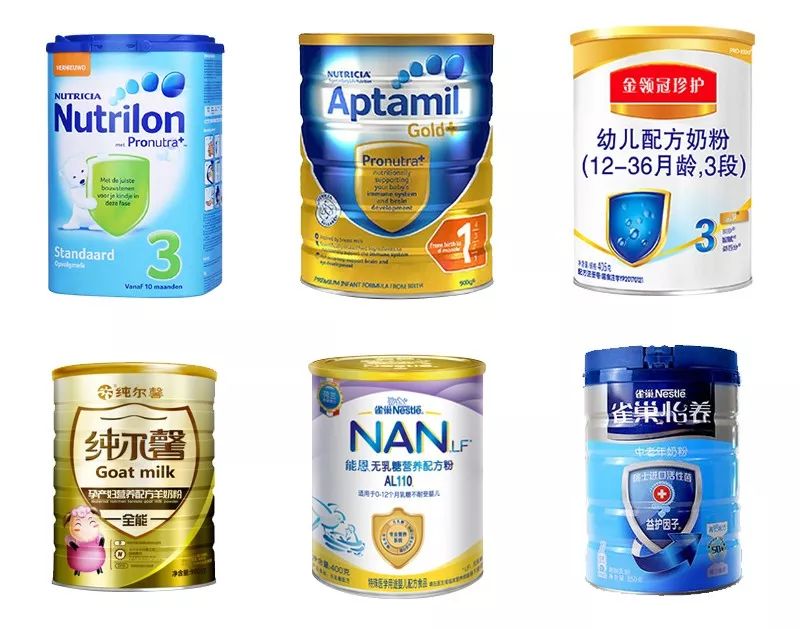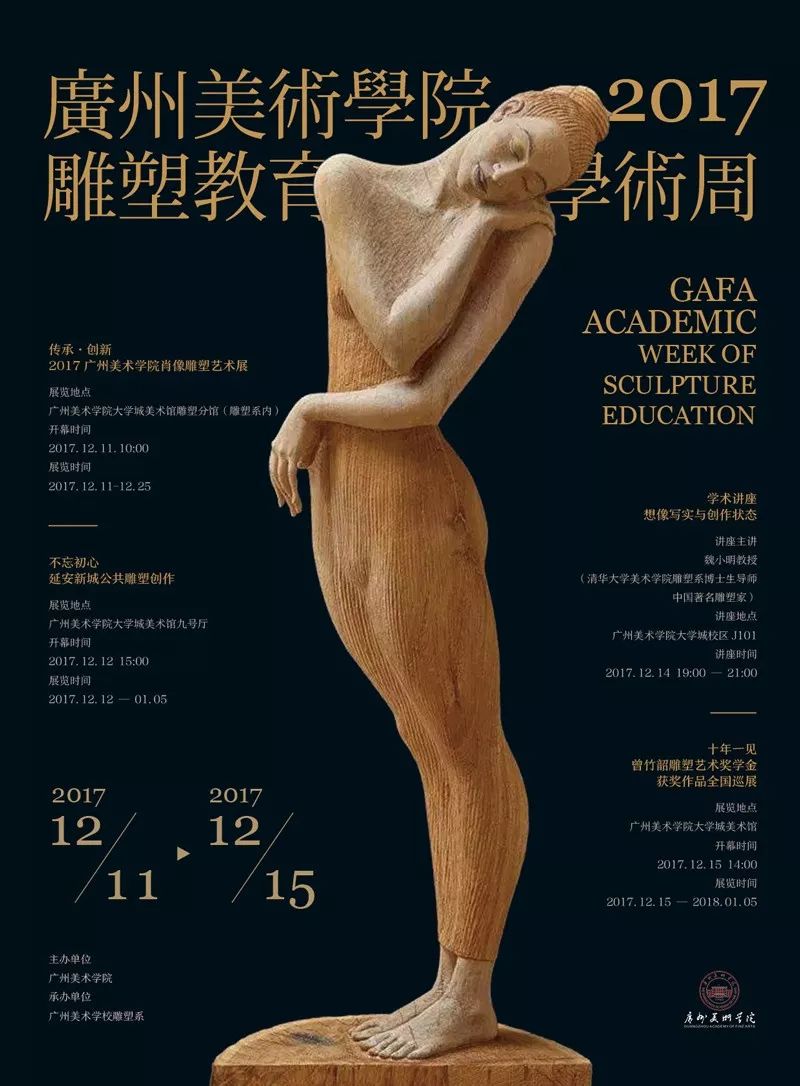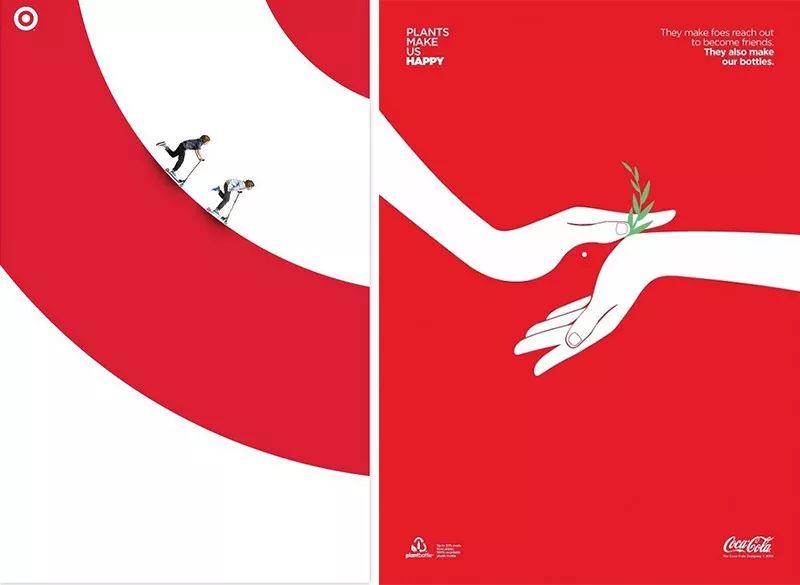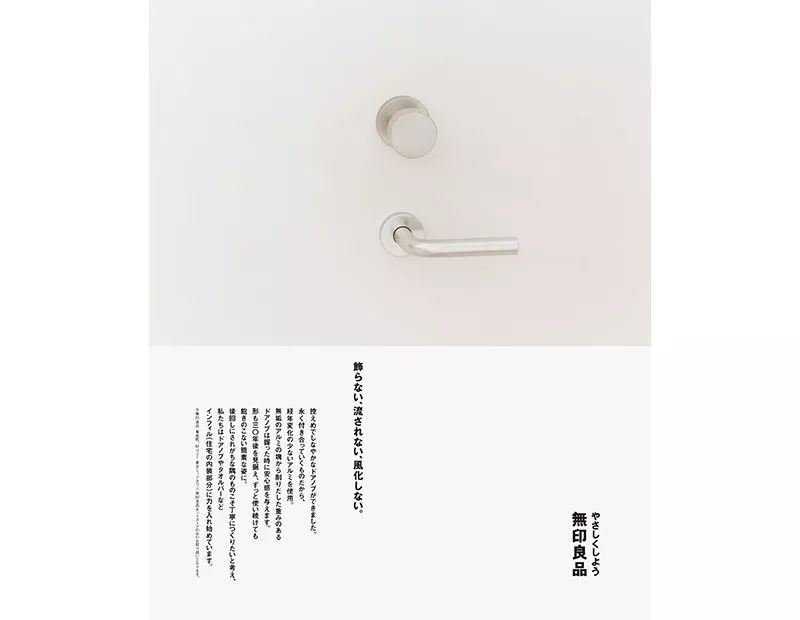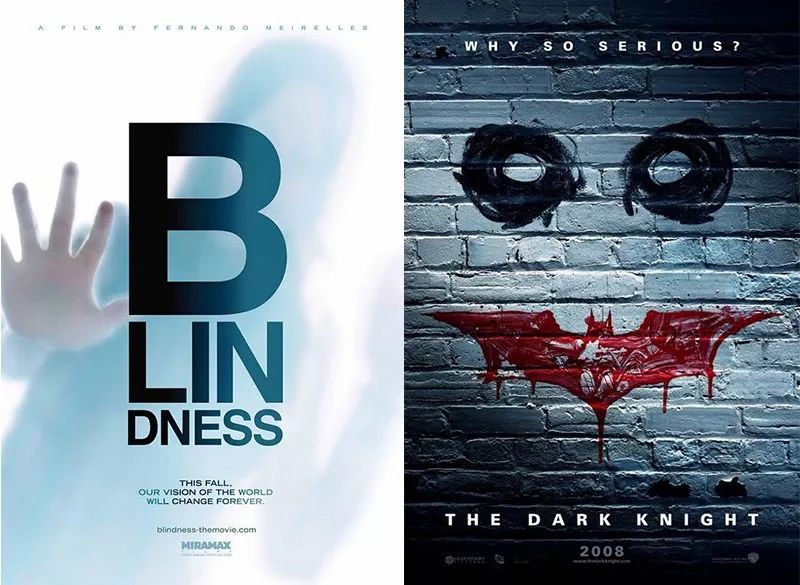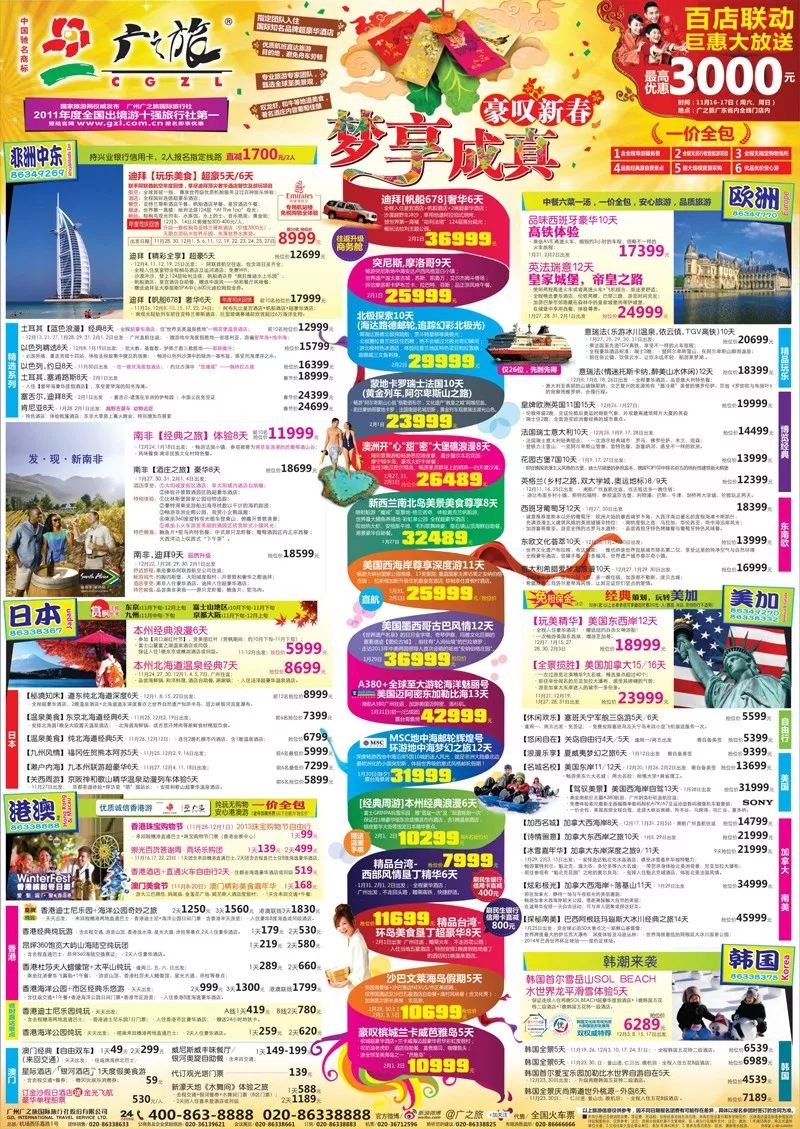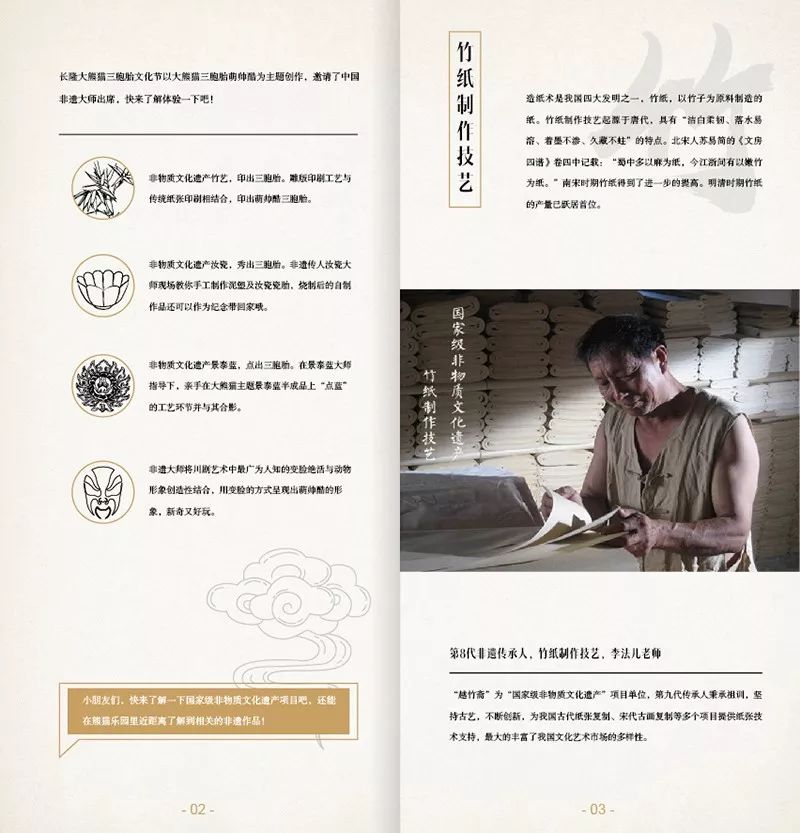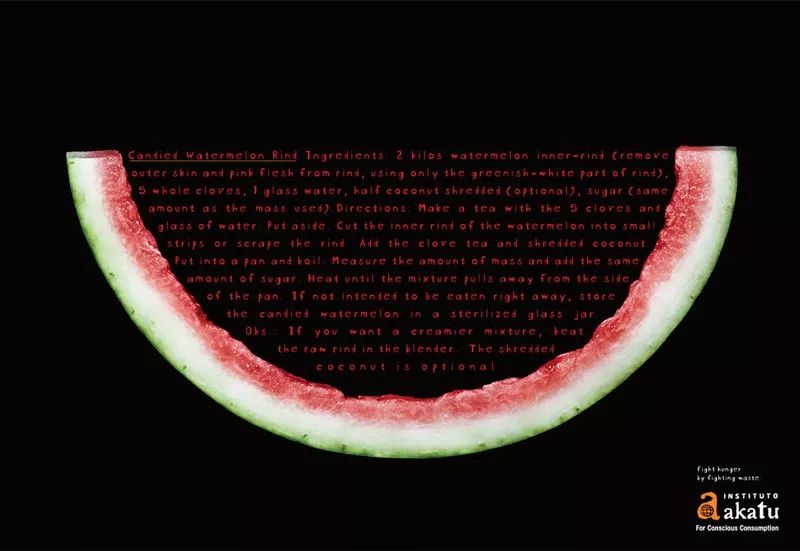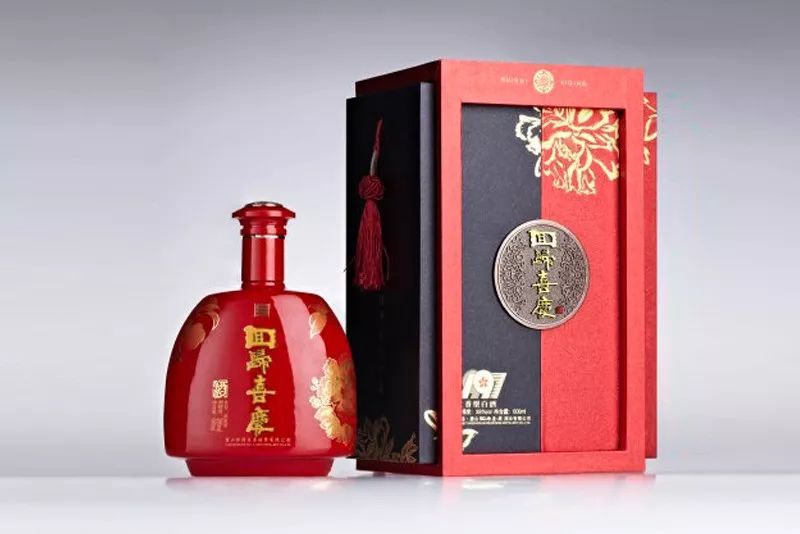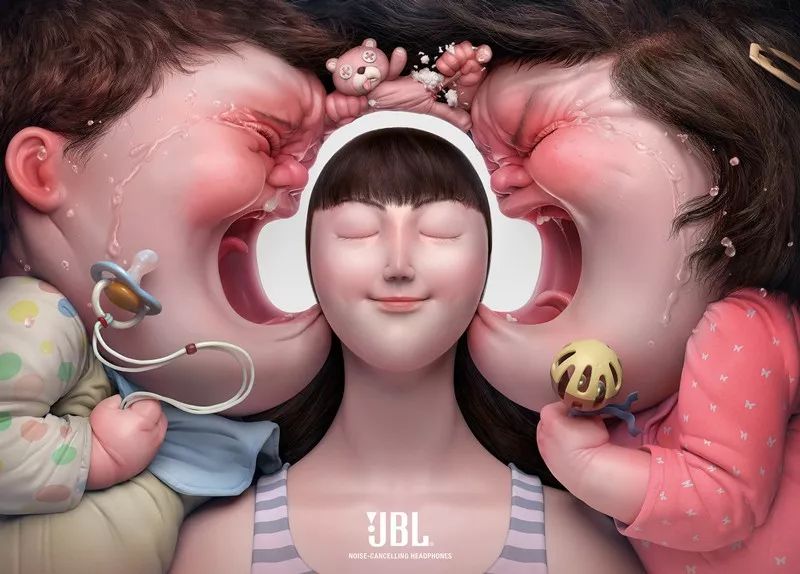
雅设计与俗设计有什么区别?
自认为还不错的设计却被别人说成很俗气,可以说是让设计师最郁闷的事情之一了,如果被说设计没创意、形式太普通、颜色太杂、排版不精致、图形不好看,或许你都能很快明白,但俗气二字总是让你摸不着头脑,不是好好的吗?怎么就俗了呢?
其实雅与俗在设计中是确实存在的,只不过它们都是一种综合感觉,没有非常具体的标准,所以比较难辨别。当然,也并非无迹可循的,葱爷算不上什么高雅人士,也做过不少俗气的设计,今天斗胆分享几点关于这个问题的看法,仅供参考。
一、俗设计与雅设计主要有
以下六方面的区别
1.大众VS新颖
大众就是指很常见、很普遍的事物,所以大众经常说的话被称为俗语,大众经常做的事情被称为习俗。在设计中也存在这一逻辑,比如说大众的色彩搭配有红配黄、红配金、红配白、蓝配白、黑配白、黑配金、黄配绿等;大众的字体有黑体、宋体、楷体等等;大众的排版方式有横排、左对齐、居中对齐、左右两端对齐等;大众的字体效果有描边字、投影字、金属字、浮雕字等等;大众的图形有矩形、圆形、椭圆形、三角形等;标志设计大众的设计形式有用品牌名的首字母做结合、用品牌名的第一个字做变形、用品牌名第一个字的首字母做变形等等。以上所举的例子在设计圈都是很大众的,从这一角度来看他们都是“俗”的。
既然我们常用的设计元素和表现形式很多都属于大众的,那该如何是好?庆幸的是,很多在某一行业里比较大众的设计事物,放到另一个行业里可能就不觉得了,所以针对具体行业来讨论这个问题会更有意义。比如地产行业非常喜欢用金色、宋体字、欧式花纹、天空、草地、树木等元素;建筑行业的Logo大多会使用建筑图形、几何图形;健康环保行业的Logo喜欢用叶子图形等;奶粉包装喜欢用盾牌、奶滴等元素;汽车广告喜欢用山川、天空、湖泊、城市建筑作为背景等。而这些元素在其他行业里可能并不大众,所以我们要经常跨行业学习。
有人可能要问了,“你的意思是只要设计中使用了大众的元素、或者大众的设计方式就会俗?”当然不是,因为很多大众的元素和做法是非常经典的,很好用且很难完全避免,比如圆形、矩形、黑白配、红白配、黑体字、宋体字、横排、左对齐等等。但如果一件设计作品中所有的元素、设计方式都很大众,又或者这件作品最核心的几大要素(如创意、配色、字体设计、图形、排版、设计形式等)是大众的,那这件作品就肯定会是一件俗气的作品,我们可以来看几个例子。
▲虽然上图的字体与排版都比较大众,但表现形式与构图比较新颖,图片也特别,所以给人的感觉并不俗。
▲上图的配色、字体、排版、构图、以及元素都比较大众,想不俗都难。
所以,想要做雅的设计,首先要拒绝过多使用大众的元素和设计套路,转而多使用一些新颖的元素、和设计形式,例如,将上图的色彩、字体和排版改变后,是不是就没那么俗了。
2.强商业VS弱商业
太过商业化的设计直观感受都很俗,好友之间我们常开玩笑:“你别跟我谈钱,俗!”你看,只要跟商业挂上勾就很难高雅起来,赚钱的意图越赤裸就越俗气。所以你看看大街上的促销广告俗吧、把自己的核心卖点重复喊的电视广告俗吧、把核心卖点都印满包装的设计俗吧,他们的共同点就是商业目的性强。
很多高雅的设计往往是非商业的,或者商业目的暴露不明显的设计,比如艺术设计、工益广告、展览海报、电影海报、品牌形象广告等等,消费者都很反感被动地接收商业信息,所以现在很多能够刷屏的广告都有地去广告化(商业化)的特点。
3.高调VS低调
跟商业紧密相连的另一个词是高调,因为商业行为都是要让传播效果最大化,所以必须高调,自然就俗了。这一点在人身上的体现也很相似,比如那些做事、说话非常高调,老是搞出大动静的人,会被说成粗鲁;而举止低调、说话慢条斯理的人,给人的感觉就比较优雅。
高调的设计就像高调的人一样,总是怕自己不够突出、不会被注意到,所以常常会做出一些不雅的举动,比如使用笔画比较粗的字体、很大的字号,使用艳丽、对比很强烈且繁杂的颜色,使用非常直白的图片,使用很多的修饰效果等。
而优雅的设计强调“不喧哗、自有声”。举个例子,很多可以拿在手里看的设计,比如名片、画册、折页、包装、Ui设计等等,字号的大小只要能让读者轻易识别(通常为6-8号)、拉开层次(信息有主次之分)就好,不一定要把所有信息拉大到占满整个版面,因为并不是字越大人们就越爱看。能够勾起人们兴趣的永远都是好看的、有趣的、与受众相关的东西,所以这才是设计师该花心思的地方。
4.繁杂VS简约
简约的设计容易显得雅,所以我们很少听见有人说苹果和无印良品的设计俗,而它们恰恰就是简约设计的代名词。
以上图海报为例,它的简约主要表现在:
1.产品(图片)简单,产品本身就是简约风格;
2.产品呈现的方式简单,没有给产品图片增加任何的修饰;
3.元素简单,画面中的元素很少,只有产品图片、Logo、以及一些文字信息;
4.颜色简单,只有黑白灰;
5.字体简单,一共只有两种字体,而且并没有给字体做任何的加工处理;
6.设计形式简单,以产品作为主体展示在画面上方,文字排列于图片下方。
7.排版简单,文字一律采用竖排,也没有借助任何元素来辅助排版。
8.留白多,版面中有近三分之一的空间内有任何元素。
正是这一系列的简单处理才造就了这类简单的设计、优雅的设计。
而很多客户都喜欢堆砌式的设计,美国著名商人约翰·沃纳梅克有一句名言:“我知道我在广告上的投资有一半是浪费的,但不知道是哪一半。”我估摸着很多客户觉得另一半的广告费是被设计中的留白浪费了,所以才把所有他们想宣传的内容都往设计里塞。
还有一些包装设计,为了凸显其产品比较高端、价格昂贵,因而喜欢在包装设计上做一堆加法,比如一款包装上有两三种以上的材料、四五种以上的工艺、包装的形式里三层外三层,这些设计就像爆发富一样,自以为高端富有,其实给人的感觉很俗。
所以,如果有人说你的设计俗,可以看看是不是做得太繁杂了,适当做些减法可能就会得到明显的改善。
5.具象VS抽象
艺术给人的感觉就很高雅,而我们常常笑说看不懂的就是艺术,由此可推出,抽象的、不直白的东西相对来说更高雅。比如我们常看到一些招贴海报表现手法很夸张、形式也很特别,甚至是其图形想要传达什么信息也不太明白,这其实是设计师运用了比较抽象的表达方式,以便使其具备一定的艺术性,这些海报设计也通常留给人雅的感觉。
还有,在一些比较权威的广告比赛中,我们很少看到类似把产品大大地放在画面中央,然后简单加上大标题和一大段内文的广告获奖,因为这些广告太普通、太直白了,也就是太俗了,而获奖的作品通常是创意巧妙,理解起来需要动点脑筋的作品。这些作品也是我们认为的雅设计。
所以,在设计中加入一点创意、采用抽象一点的配图和设计形式,也能增加设计高雅的气质。
6.没细节VS有细节
有细节的设计更精致更有设计感,所以感觉比较雅,而没细节的设计比较粗糙、不经看,所以显得俗。
比如在设计画册时,除了把视觉流程梳理好、把视觉层次拉开、把各必要元素的布局确定以及选择好配色后,还需要想想,再做些什么工作可以使设计更精致、更吸引人。
以上图为例,我们可以把白色背景改为有点纸纹的背景,以增加画册的文化氛围,左边图标和右边小标题的线框颜色可以改为金色,以呼应左下角的金属块,增加颜色的丰富性、在右上角的文字下面可以压一个浅灰色的书法字,来增强版面的层次感,以及可以把右边的配图延伸到边界线处,打破版心的束缚。做完一系列微小的调整后,整体效果是不是比之前更雅了?
二、俗的设计不一定是差设计
俗的设计有很多缺点,但并不是说俗的设计就一定是差设计,俗的另一种解释是接地气,即更贴近人与生活,所以很多俗的设计在传播、转化效率方面,反而比一些所谓的雅设计效果更佳。还有些品牌,它们的定位就比较接地气,如果把它的设计做得太高雅,不仅与品牌定位背道而驰,也很难有好的效果。
俗的设计也不一定是很丑的设计,只不过可能存在太大众、商业气息比较浓、或者太繁杂等问题,并没能达到愉悦视觉的效果。还有些设计是因为用错了地方所以才显得俗,比如用调性年轻时尚的高饱和度渐变色,去做面向中年人的高端品牌设计,也会被当作是俗的设计。
三、俗的设计也不一定是有效的设计
当被批设计太俗气时,很多甲方或者设计师都会用实效性来作挡箭牌,说什么把设计做得再好看再高雅也没用,关键是要有效。按照他们的逻辑似乎是,只要把设计做俗了就会有效,做雅了就没有效果了。
显然不对!低俗、丑陋且效果差的设计比比皆是,这一点并不难解释,因为俗的设计太大众,所以很难在众多设计中引起消费者的注意;因为俗的设计商业目的太赤裸,所以更容易令人反感;因为俗的设计不够美观、没有内涵,所以很难给产品和品牌带来附加值。
上图店招设计的效果一定比下图的好吗?我看未必,但是上图的设计比下图丑、比下图俗气是显而易见的。
我知道俗的设计会一直存在,因为俗并不一定会影响设计完成其基本功能,更因为俗与雅是相对的,没有俗就无所谓雅,就像美与丑一样。但雅而有效的设计才是设计师需要一直追求的,因为优秀的设计除了能传达信息、卖货以外,还有责任帮助品牌长期发展、以及正确引导人们的审美。